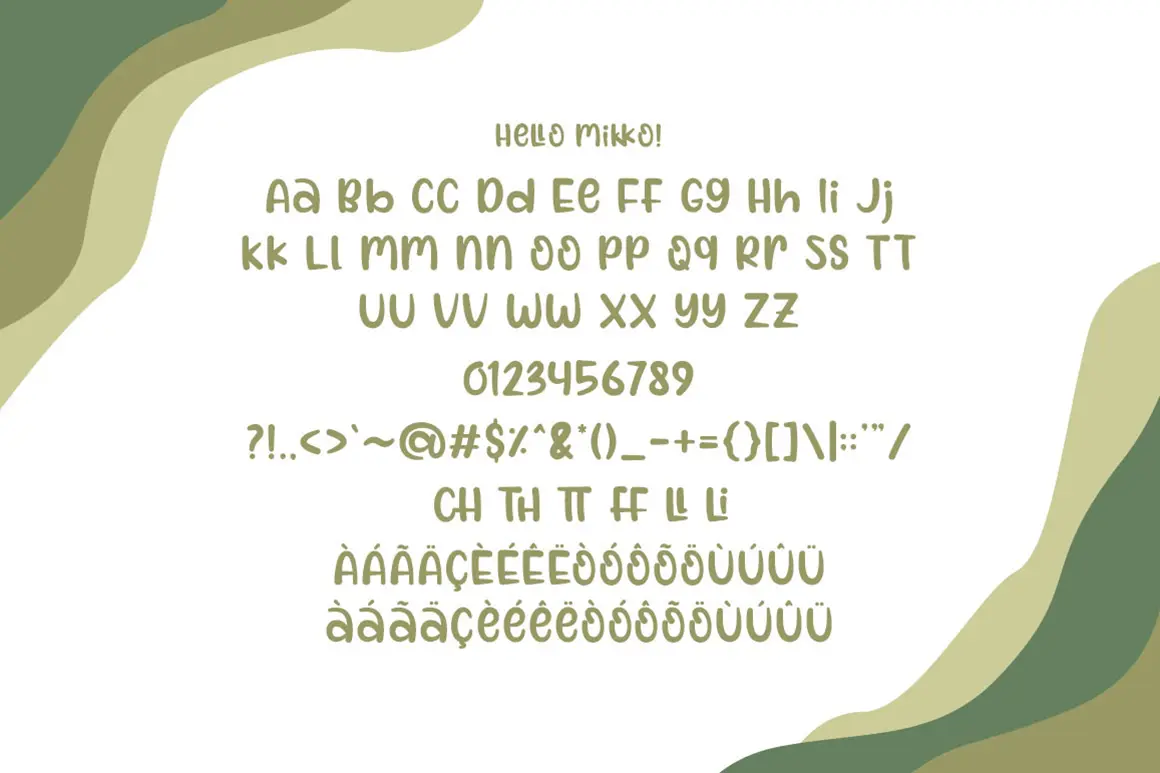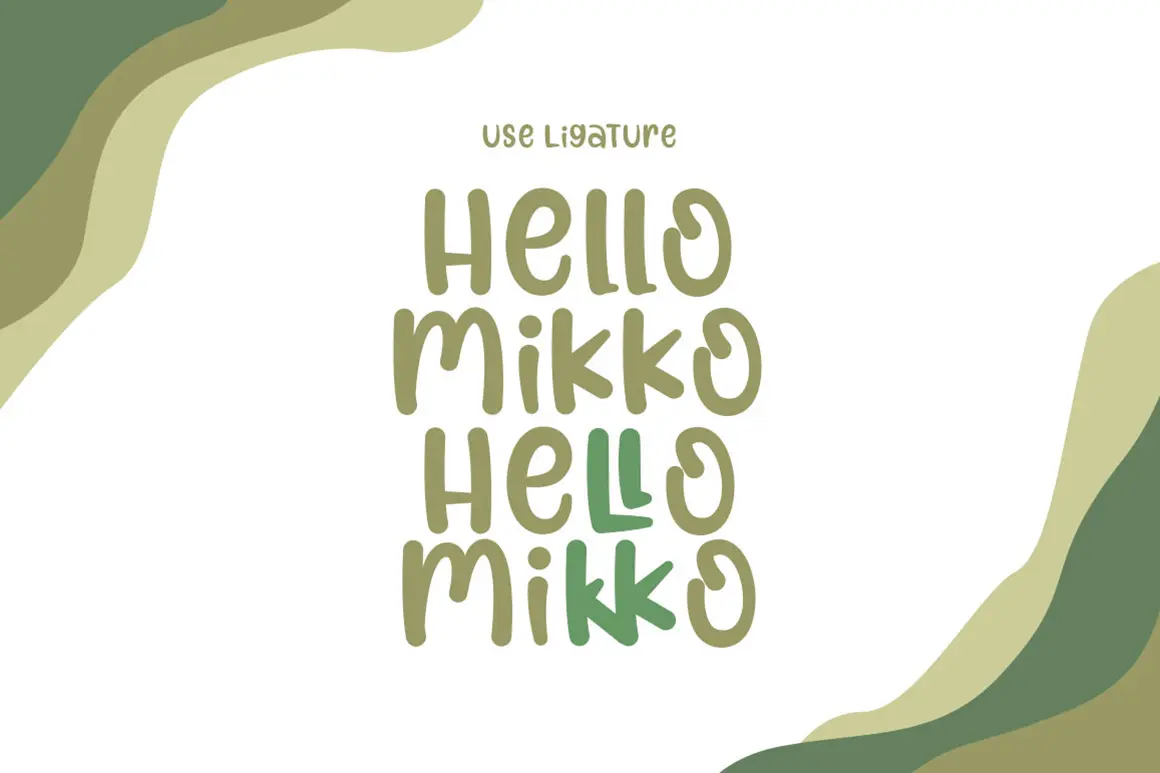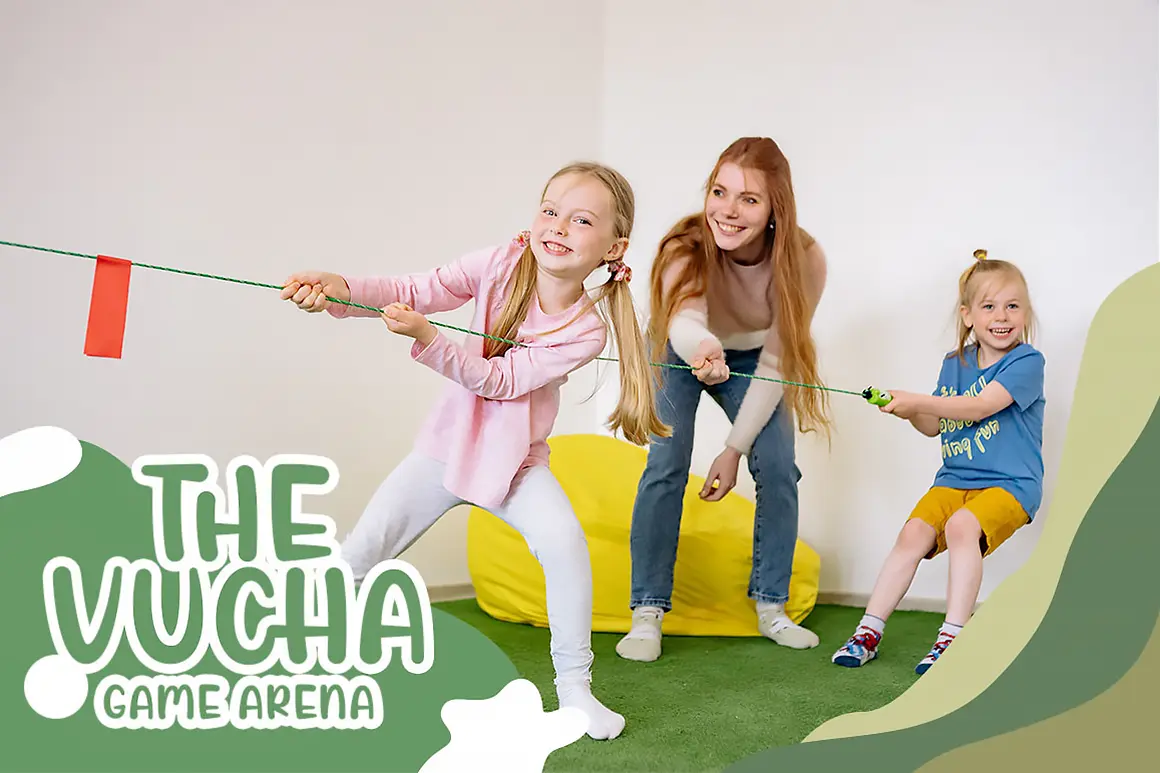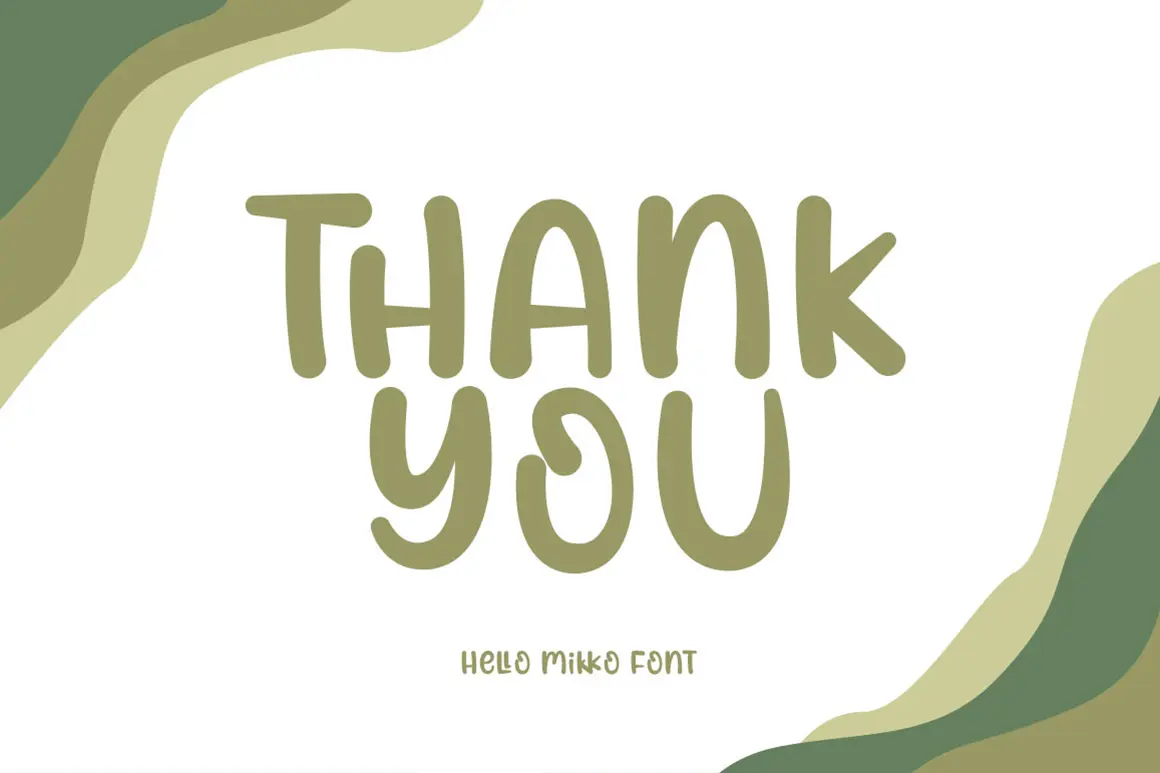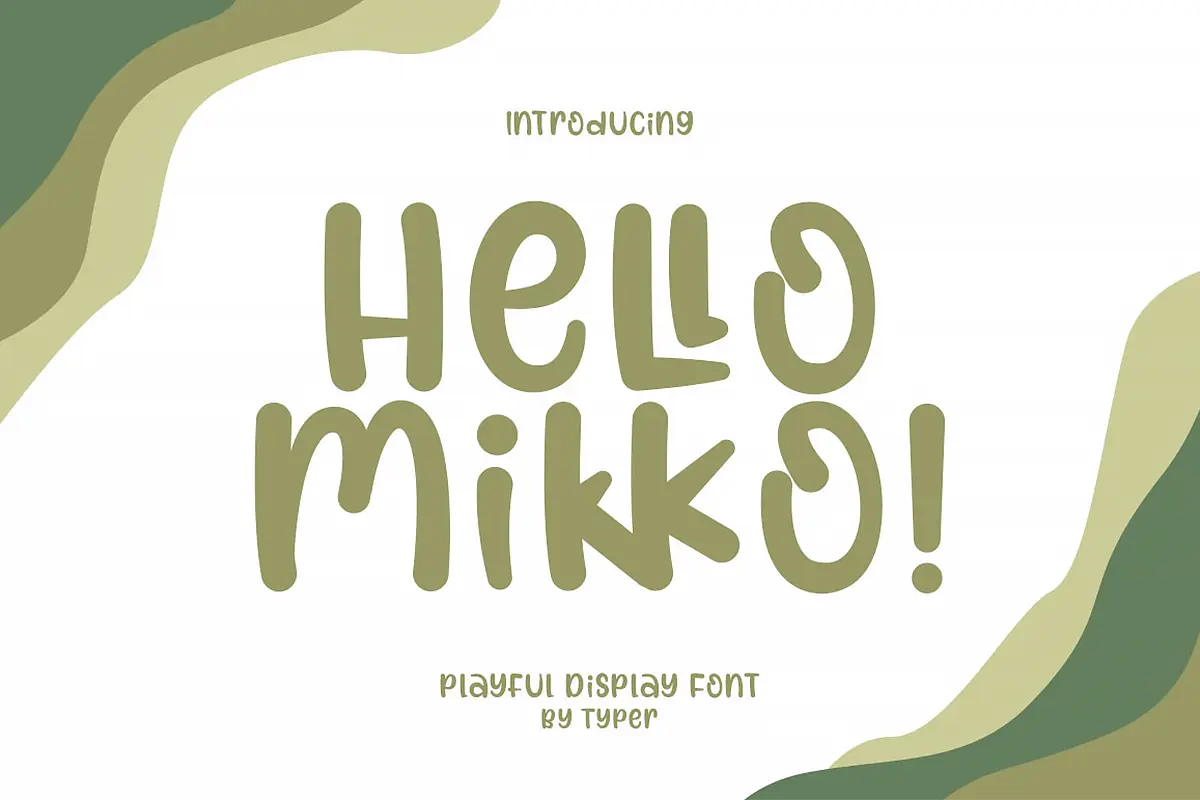
فونت بامزه و کودکانه
فونت Hello Mikko یک فونت نمایشی بامزه، دوستانه و غیررسمی است که میتونه به طراحیهای شما حس صمیمیت و شادی بده. این فونت برای پروژههای خلاقانه عالیه و بهسرعت میتونه به فونت محبوب و پرکاربردت تبدیل بشه.
⭐ ویژگیهای محصول
- فونت نمایشی با سبک دوستانه و غیررسمی
- مناسب برای پروژههای خلاقانه و سرگرمکننده
- خوانایی بالا و طراحی جذاب
🎯 موارد استفاده
- طراحی کاردستیها و پروژههای کودکانه
- ساخت کارتهای تبریک و دعوتنامهها
- استفاده در پرزنتیشنها و اسلایدهای آموزشی
- تزئین محتوای دیجیتال و شبکههای اجتماعی